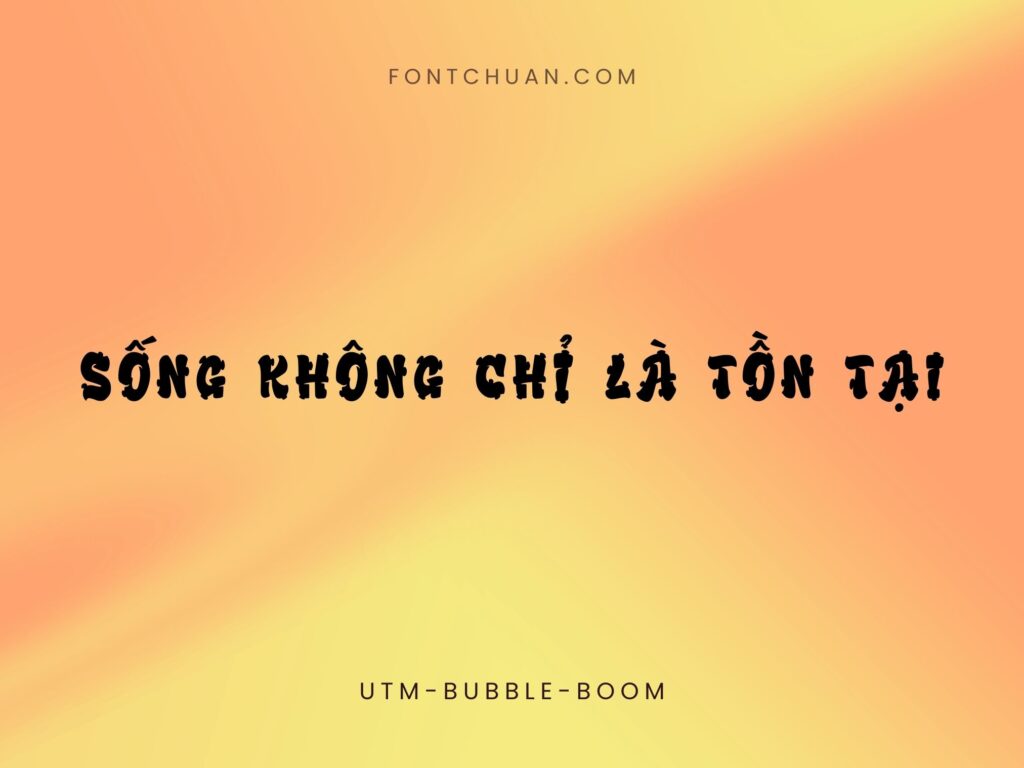
Font UTM Bubble Boom Việt Hóa
UTM Bubble Boom là phiên bản Việt hóa của font chữ Bubble Boom, một kiểu chữ graffiti được thiết kế bởi Blankids Studio. Font này nổi bật với các ký tự tròn trịa, đường nét dày dặn và phong cách vui nhộn, tạo cảm giác năng động và trẻ trung. Phiên bản Việt hóa đã được thực hiện bởi Unicode Thiên Minh, hỗ trợ đầy đủ tiếng Việt cùng hơn 100 ngôn ngữ khác. Đây là một trong những font được cộng đồng thiết kế sưu tầm và chọn lọc nhằm đáp ứng nhu cầu đa dạng trong thiết kế.
Mặc dù mang hơi hướng graffiti, UTM Bubble Boom vẫn có thể được xem là một biến thể sáng tạo của Font Handwritten, nhờ vào những đường nét tự nhiên, phóng khoáng và cá tính mà nó thể hiện. Điều này giúp font trở nên linh hoạt hơn khi được ứng dụng trong các thiết kế cần sự tươi trẻ nhưng vẫn gần gũi và thân thiện.
UTM Bubble Boom có cấu trúc chữ với các nét tròn đều và độ dày đồng nhất, tạo nên sự hài hòa và dễ nhìn. Font này phù hợp cho các ứng dụng như thiết kế tiêu đề, logo, bao bì sản phẩm và các ấn phẩm in ấn yêu cầu sự vui nhộn và nổi bật. Các ngành nghề như quảng cáo, giáo dục, công nghệ và bất động sản có thể tận dụng UTM Bubble Boom để tạo điểm nhấn độc đáo trong thiết kế.